我们今天向大家介绍的是一位农民书法家,他是个残疾人,但他身残志坚持苦练书法30年,一手楷书实力出众,最终他的楷书被中华字体库所收录,展现出强大的个人魅力,这位老人家就是仕金正。
学习书法是很有吸引力的一件事,当你对他产生兴趣,想忘都忘不了。但是,学习书法的过程是很枯燥乏味的,如果没有很好的毅力,是坚持不下去的。而仕金正是一位残疾人,他失去了他的右手,而且没有稳定的收入,所需对于他来说学习书法更加的艰难的事,但是功夫不负有心人,仕金正完成了他人生的逆袭,不仅把书法写好了,而且功成名就。
仕金正是1963年生人,家庭条件一般,是一位普普通通的农民,他的工作是在一家窑场搬砖。在他19岁的时候,不幸被机器把右手绞断,就这样变成了残疾人。仕金正明白即是失去了胳膊也要生活,也要为生活拼搏。刚开始时仕金正接受不了这样残酷的现实,但是即是他迷茫和痛苦,他也没有被这场变故所击败,后来他凭着坚强的意志,找到了自己的价值,找到了一个让自己有成就感的兴趣——书法。
仕金正开始接触书法是90年代初,到现在他已经学习了30几年的书法,由于他的右胳膊没了,毕竟不是左撇子,他等于从新开始,必须习惯用左手做事,在他初学书法的10年里,他几乎都是在适应自己一个人的左手。所以,仕金正白天为了工作生活,利用业务的时间练习书法,不知不觉中书法成了他生活的一部分。
对仕金正书法帮助很大的要说他们当地的一位书法家,一次偶然的机会认识了这位书法家,并收仕金正为学生,指点他书法,就这样他就开始在正式的学起了书法,而教他书法这位书法家正是楷书高手——王玉宽。
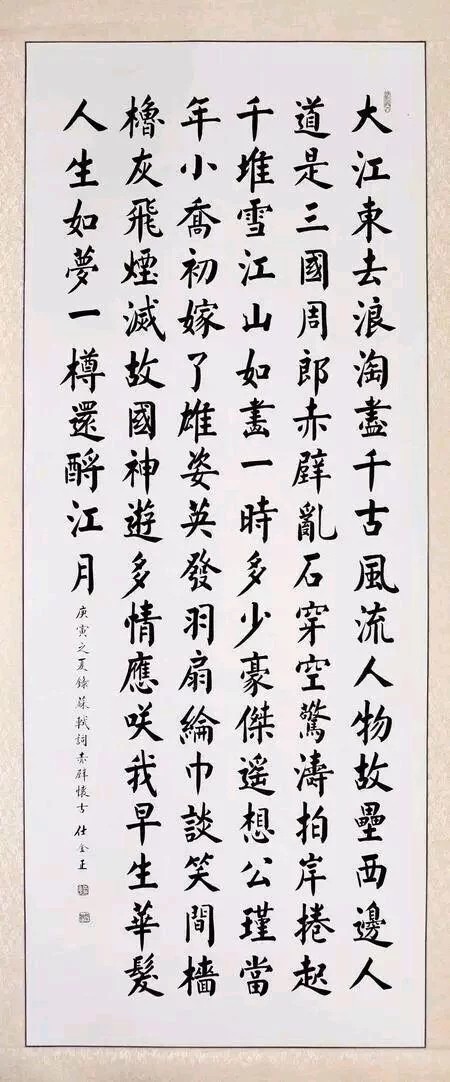
功夫不负有心人,老师的指点加上自己坚持不懈的努力,仕金正开始在书法上发光,于2005年参加山东书协展览并入展,于是他开始走上职业书法家的道路。后来仕金正更是凭着书法的魅力娶了一位比自己小10岁的媳妇,成为了他的贤内助。
随着时间一点一滴的流逝,到了2017年,一家公司找上仕金正,他们请仕金正写一套楷书字模,用于录入中华字体库。仕金正答应以后就开始工作起来,在完成之前几乎每天都要写几个小时,把大部分时间都用在上面,为了写好这套字摹,仕金正写坏了多枝毛笔,最后完成下来写了9300字的字模,可见仕金正用了多大的功夫去完成的。
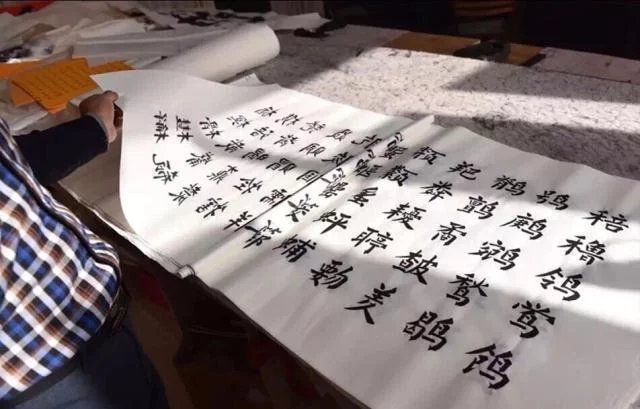
从仕金正的事迹可以明白一个道理:“只要有信心,铁杵磨成针。”像仕金正这样从失去适应的右手,习惯左手不知适应了不久,经历了多少的艰难,但是他还是成功了,写的了一手漂亮的毛笔字。和仕金正相比我们不知幸运了多少,还有什么理由不好好学习呐!